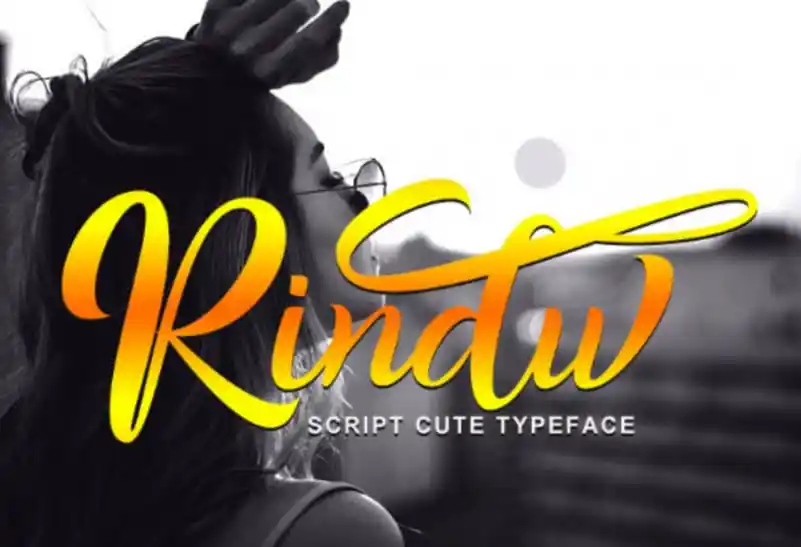
Rindu Calligraphy Typeface – Download Grátis
A Rindu Calligraphy Typeface é uma fonte que traz um estilo único para quem busca personalidade e originalidade no design. Ideal tanto para projetos pessoais quanto profissionais, esta fonte está perfeitamente adaptada para diversas finalidades como: cartões de apresentação, capas de blog, assinaturas em editoriais de moda, embalagens, convites, selos e materiais gráficos em geral. Sujeito a ser usado também nas criações visuais que requerem um toque distintivo e elegante, esta fonte é uma escolha excepcional tanto para novatos quanto para designers mais experientes. Com sua riqueza de detalhes e elegância, Rindu Calligraphy Typeface se destaca em qualquer projeto onde deseja transmitir identidade visual única e expressão pessoal.